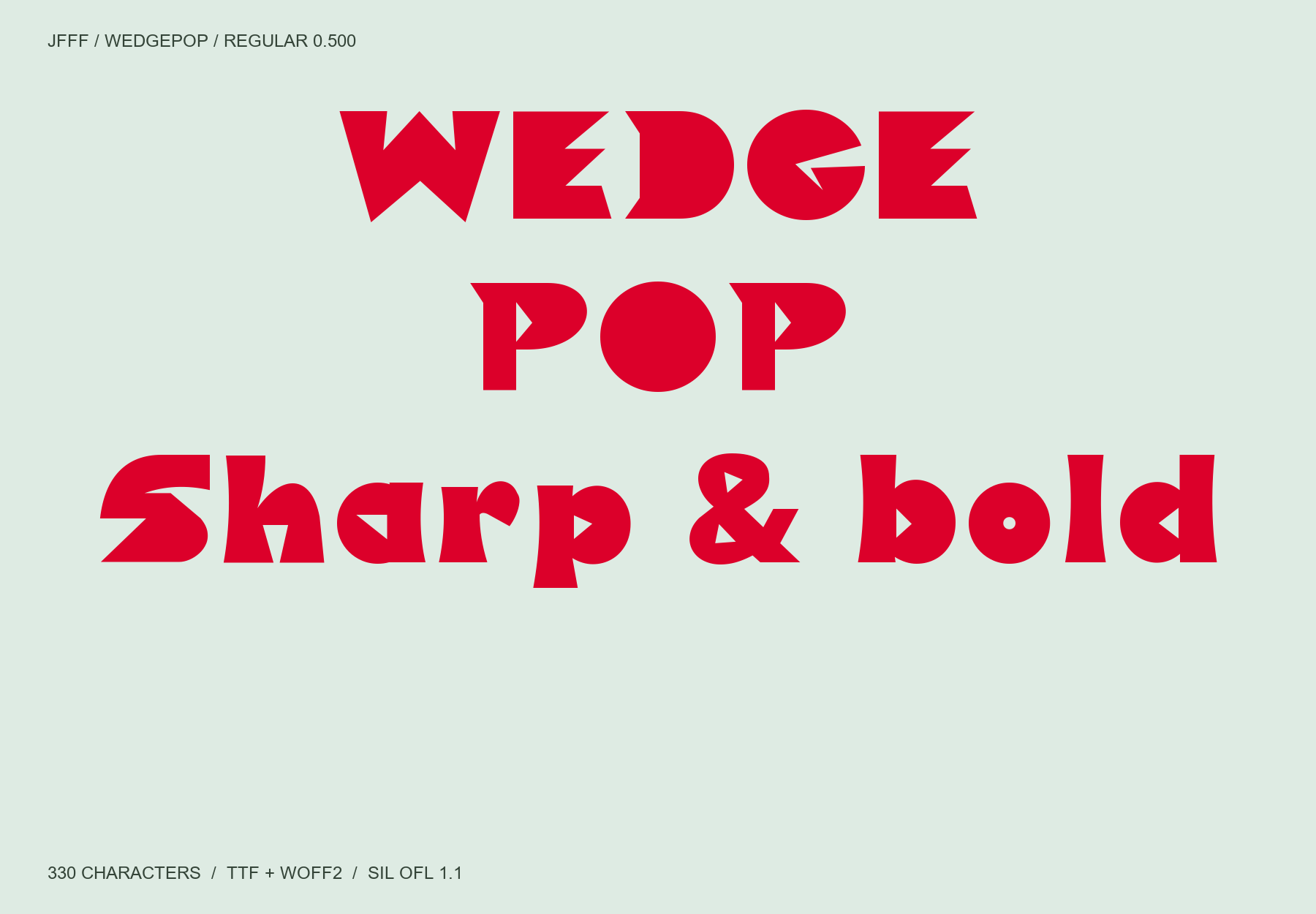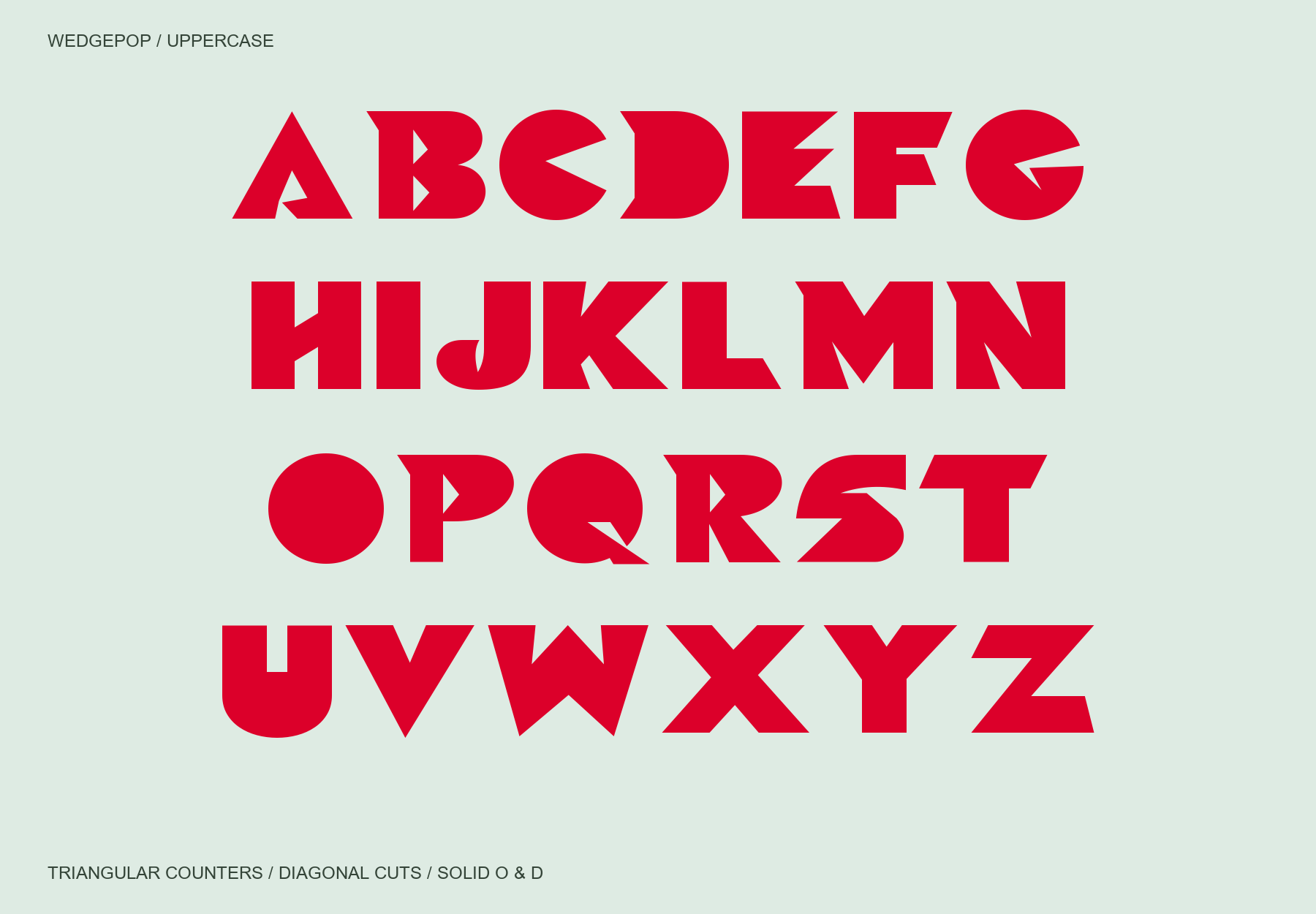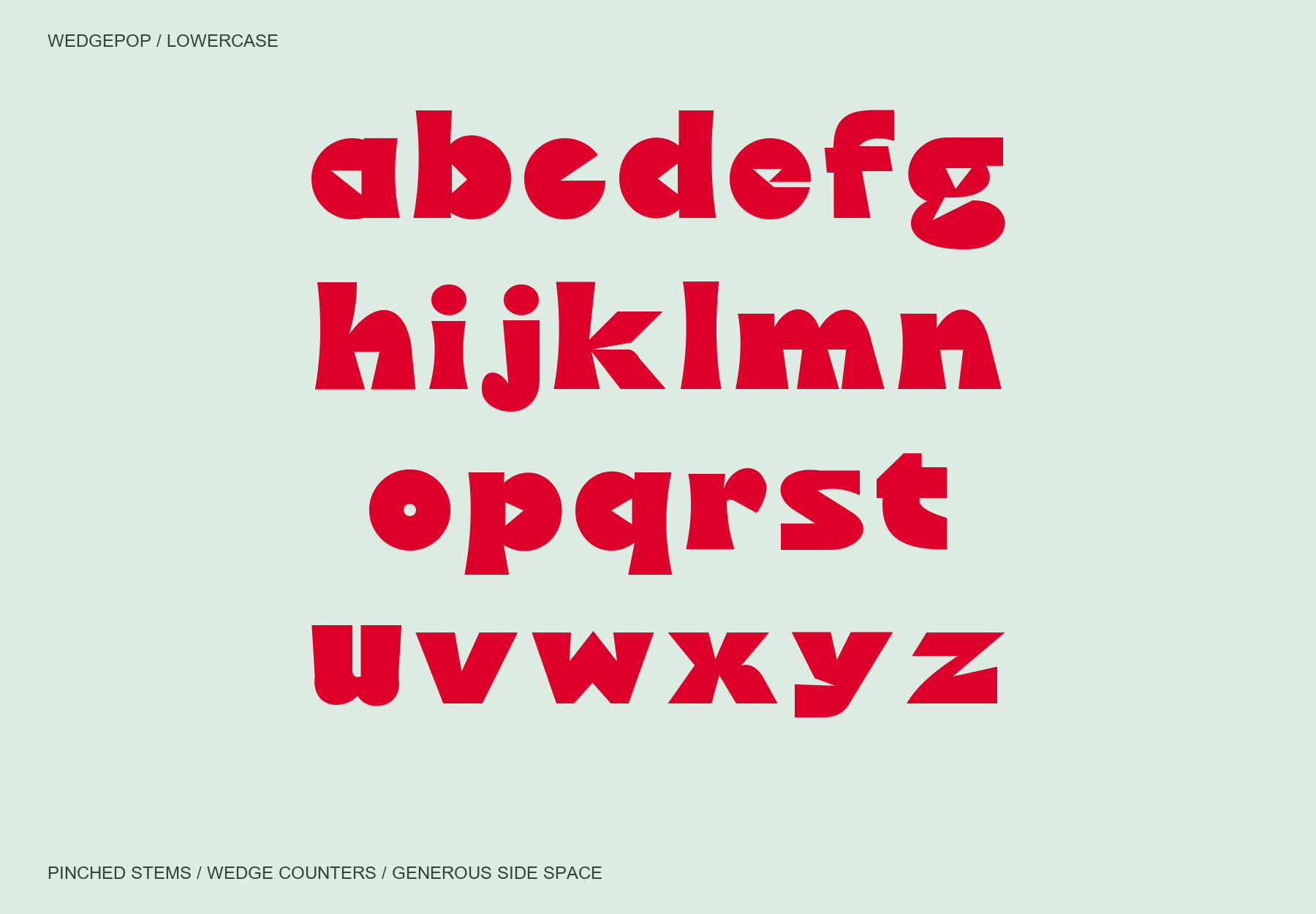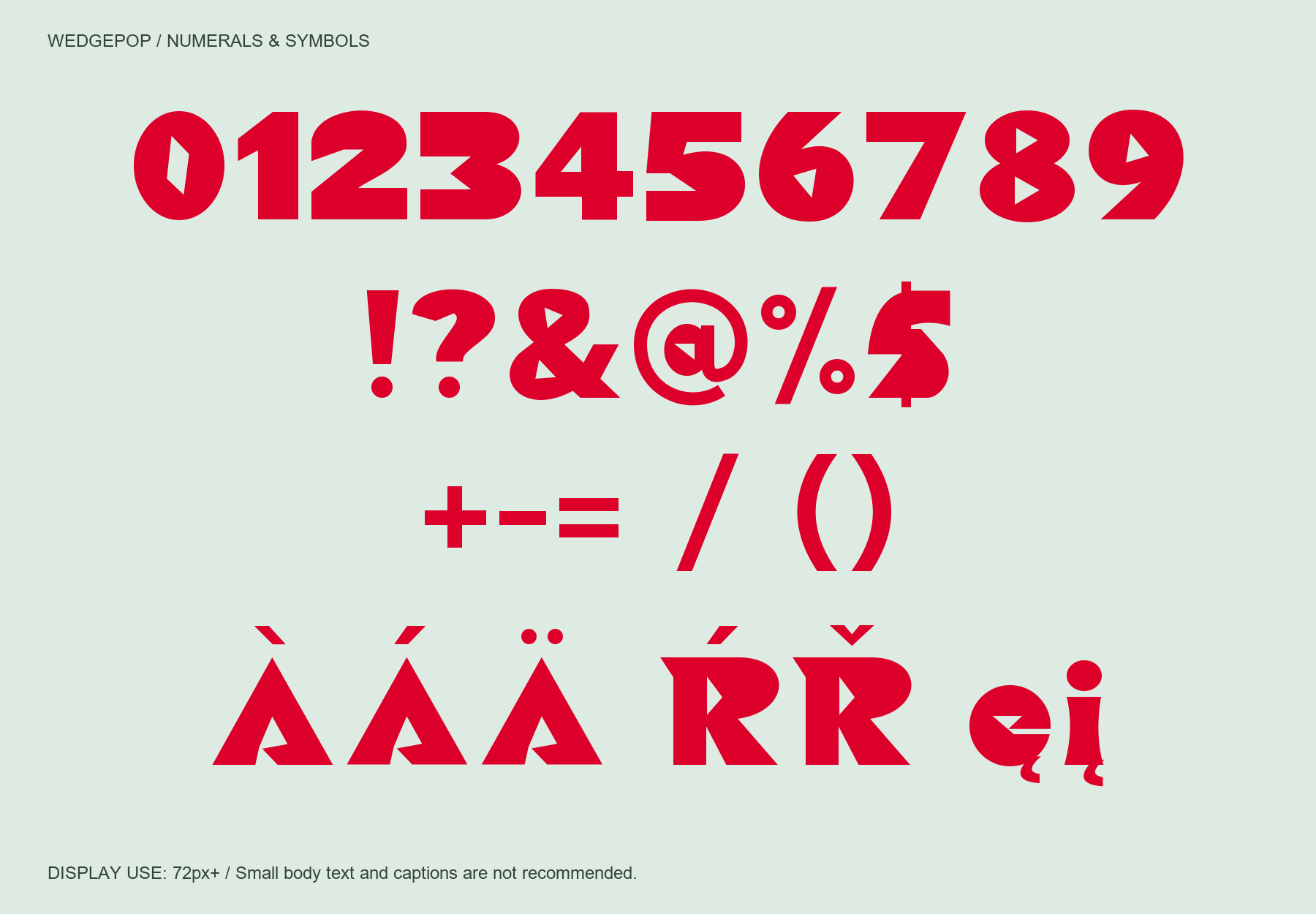
Wedgepop은 원형 덩어리와 삼각형 속공간, 날카로운 사선 절단을 결합한 초굵은 기하학적 디스플레이 서체입니다. 대문자 O·D의 꽉 찬 실루엣, A·C·G의 쐐기 모양, 소문자의 잘록한 기둥과 넓은 끝부분이 강한 인상을 만듭니다. Regular 0.500 · 라틴 330자(공백·NBSP 2자 포함). 영문 대소문자, 숫자, 확장 라틴 악센트와 기호를 지원하며 한글은 포함하지 않습니다. TTF와 WOFF2를 하나의 ZIP으로 제공하고 SIL Open Font License 1.1로 무료 배포합니다. 72px 이상 제목·포스터·패키지에 권장합니다. 작은 본문·캡션에서는 좁은 속공간과 절단면이 약해지므로 권장하지 않습니다. 원형으로 채운 O·D는 이 서체의 의도된 특징입니다. 330자 확대 표본 검토 후 34자의 조형을 다듬었으며, 0.500에는 악센트 변형을 포함한 791쌍의 커닝과 괄호 메트릭 수정을 반영했습니다. 108,900개 인접 조합의 윤곽 경계 충돌 검사에서 충돌은 발견되지 않았습니다. 이는 모든 조합을 수작업으로 커닝했다는 뜻은 아닙니다. Windows 네이티브 출력과 Edge·Chrome의 웹폰트 로딩·커닝을 확인했습니다. macOS·iOS Safari 및 Adobe·Office 앱 UI는 미검수입니다.